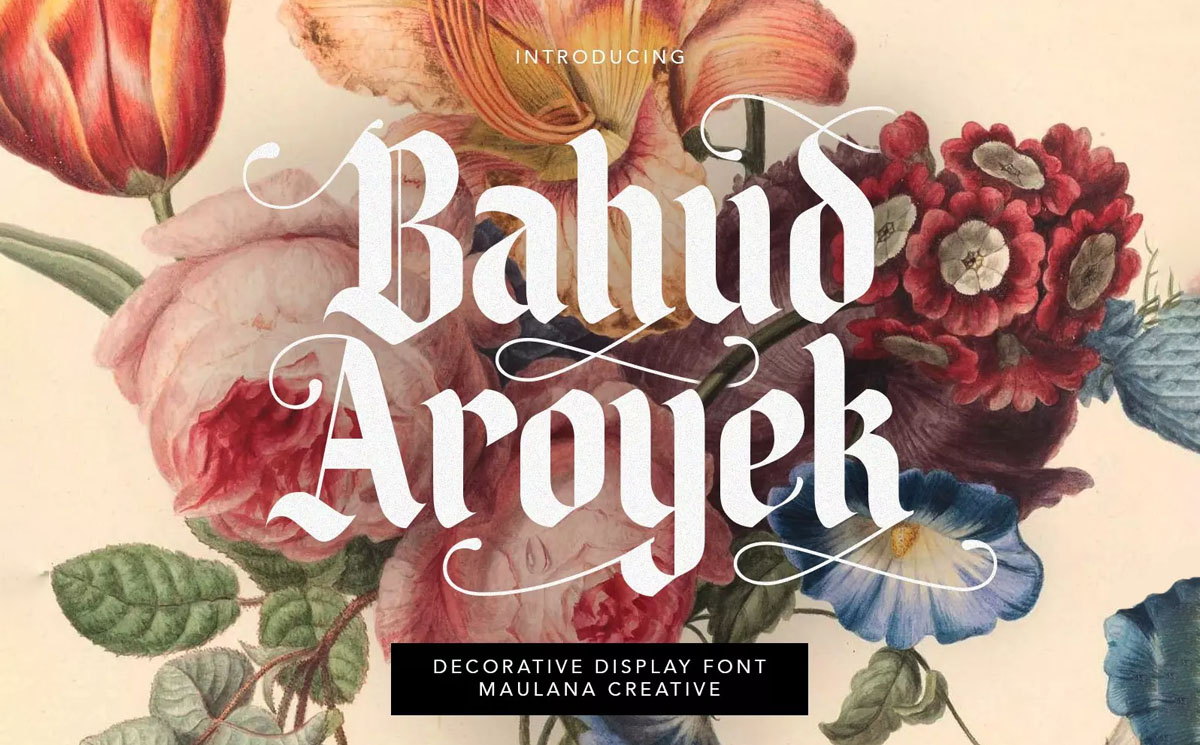
Khám Phá Font Chữ Cổ Điển Vintage SVN Bahud Aroyek
Nếu bạn đang tìm kiếm một chất liệu thiết kế mang đậm hơi thở của thời gian, font chữ cổ điển vintage SVN Bahud Aroyek chính là mảnh ghép hoàn hảo. Với phong cách retro đặc trưng, bộ phông chữ này không chỉ gợi nhớ về những thập niên trước mà còn mang lại sự sang trọng, bí ẩn và đầy nghệ thuật cho mọi ấn phẩm. Đặc biệt, với tiền tố “SVN”, đây là phiên bản đã được Việt hóa chỉn chu, giúp các designer Việt thoải mái sáng tạo mà không lo rào cản về ngôn ngữ.
Những Đặc Điểm Nổi Bật Của SVN Bahud Aroyek
Sự quyến rũ của SVN Bahud Aroyek nằm ở sự kết hợp khéo léo giữa nét cổ điển và tính ứng dụng hiện đại:
• Phong cách Vintage đặc trưng: Các đường nét được thiết kế tinh xảo, mang lại cảm giác hoài cổ, mộc mạc nhưng vô cùng cuốn hút.
• Chi tiết trang trí tỉ mỉ: Sự nhấn nhá ở các con chữ giúp tổng thể đoạn text trở thành một tác phẩm nghệ thuật typography thực thụ, không bị nhàm chán.
• Việt hóa chuẩn Unicode: Các dấu câu tiếng Việt được tác giả tinh chỉnh kỹ lưỡng, đảm bảo sự cân đối, không bị gãy nét hay lệch định dạng khi gõ các cụm từ dài.
• Hiệu ứng thị giác mạnh mẽ: Cực kỳ nổi bật khi được sử dụng ở kích thước lớn (Heading) hoặc kết hợp với các hiệu ứng in dập nổi, texture cũ kỹ.
Ứng Dụng Hoàn Hảo Trong Thiết Kế Đồ Họa
Với tinh thần hoài cổ đậm nét, SVN Bahud Aroyek là “vũ khí” đắc lực cho các dự án thiết kế mang phong cách retro hoặc classic:
• Bộ nhận diện thương hiệu: Rất phù hợp cho logo quán cà phê acoustic, tiệm bánh thủ công, tiệm cắt tóc nam (barbershop) hoặc các thương hiệu thời trang vintage.
• Thiết kế bao bì: Tạo ấn tượng mạnh trên các nhãn mác sản phẩm thủ công, rượu vang, xì gà, hay các hộp quà tặng cao cấp mang phong cách cổ điển.
• Ấn phẩm truyền thông & Nghệ thuật: Là lựa chọn tuyệt vời cho poster phim ảnh, bìa sách, typography trích dẫn, hay thiệp cưới mang phong cách mộc mạc (rustic).